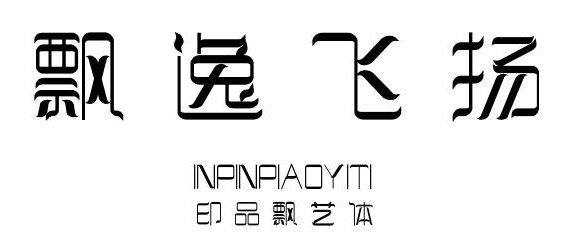
印品飄藝體是一款形似絲帶的義啟字體,充滿了藝術(shù)字體的美感和特色,讓文字更加清新別致,給人十足的新鮮感,讓你的設(shè)計(jì)更增獨(dú)特魅力,綠色資源網(wǎng)今日推薦!
一款自帶美顏效果的字體。從橫撇點(diǎn)勾處做了仿絲帶設(shè)計(jì),字里行間不再肉,細(xì)節(jié)處醒目突出,讓字體自帶飄逸飛揚(yáng)的自由感。給人一種簡(jiǎn)約的美感,滿滿的藝術(shù)氣息。
印品飄藝字體是印品系列中最為飄逸飛揚(yáng)的pop字體,整體設(shè)計(jì)讓文字更加生動(dòng)活潑,流動(dòng)的線條和圓潤(rùn)的筆觸讓人眼前一亮,用在包裝設(shè)計(jì)、平面設(shè)計(jì)上面能為作品增色。